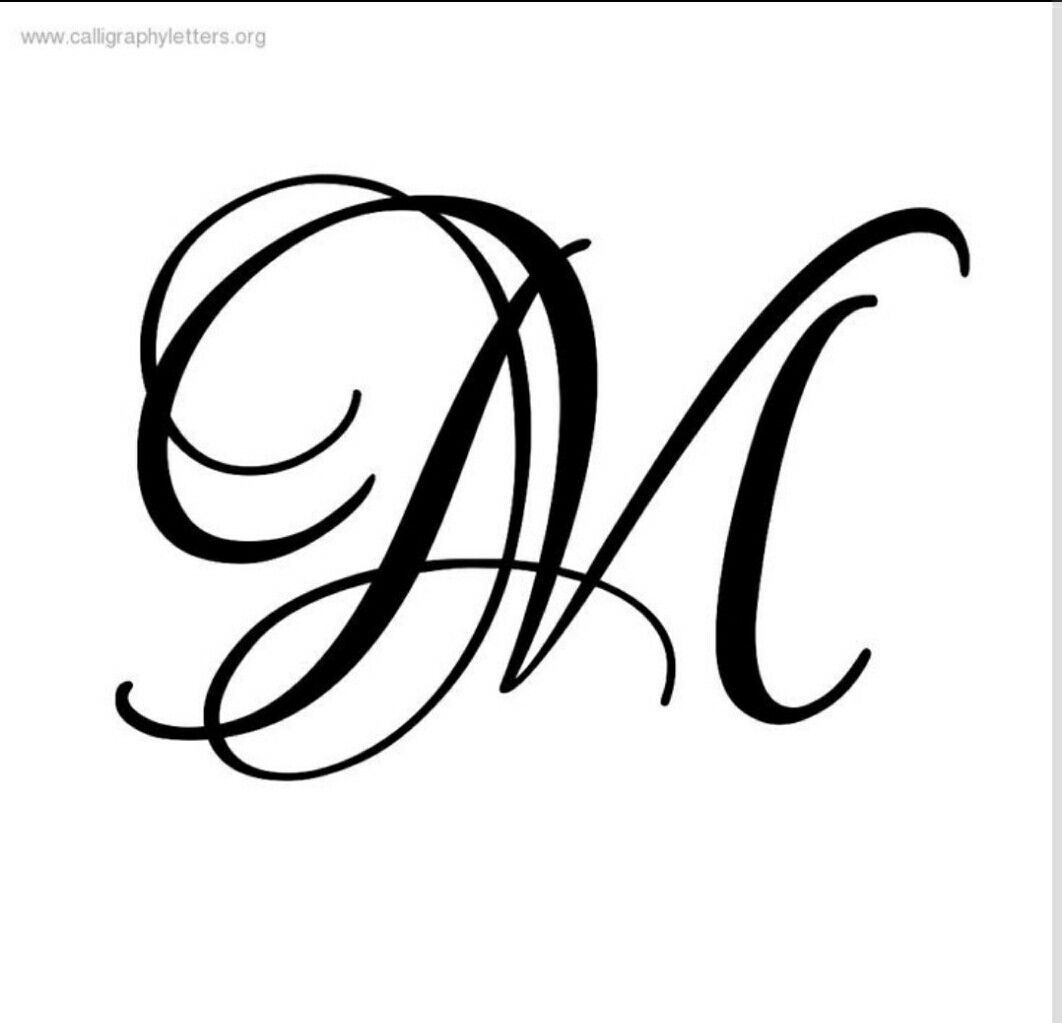
Как выбрать красивый шрифт для вашего онлайн-контента
Введение: Шрифты играют важную роль в эстетике и читабельности текста. Они могут воздействовать на наше восприятие информации и вызывать различные эмоции. В современном онлайн-контенте все больше людей обращают внимание на использование красивых шрифтов, чтобы сделать свой контент более привлекательным и запоминающимся.
1. Важность выбора правильного шрифта: Когда дело доходит до создания контента для веб-сайта, блога или социальных медиа, правильный выбор шрифта может повысить его эффективность и уникальность. Красивый шрифт поможет привлечь внимание читателей и сделать ваш контент более привлекательным.
2. Популярность использования красивых шрифтов: В последние годы наблюдается растущая
популярность использования красивых шрифтов в онлайн-контенте. Бренды, блогеры и дизайнеры все больше обращаются
к уникальным и привлекательным шрифтам, чтобы выделиться среди конкурентов и установить свой узнаваемый стиль.
3. Онлайн-сервисы по поиску и созданию шрифтов: Существует множество онлайн-сервисов, которые предлагают широкий выбор красивых шрифтов для использования в вашем онлайн-контенте. Некоторые из них предоставляют бесплатные шрифты, а другие — платные. Вы можете исследовать различные сервисы, чтобы найти идеальный шрифт, соответствующий вашему стилю и потребностям.
Как выбрать и использовать красивый шрифт
1. Определите свою аудиторию и цель: Перед выбором шрифта определите свою целевую аудиторию и цель вашего контента. Если ваша аудитория молодежь или веб-дизайнеры, то вы можете рассмотреть современные и стильные шрифты. Если ваш контент официальный или деловой, то лучше выбрать более классический и профессиональный шрифт.
2. Учитывайте читабельность: Независимо от выбранного шрифта, обязательно учтите его
читабельность. Шрифт должен быть легким для чтения и понимания.
Избегайте слишком узких или слишком декоративных
шрифтов, которые могут затруднять восприятие текста.
3. Используйте шрифты согласно их назначению: Некоторые шрифты лучше подходят для заголовков и выделения основных идей, в то время как другие шрифты лучше подходят для основного текста. Используйте разные шрифты, чтобы создать контраст и иерархию в вашем контенте.
4. Не перебарщивайте с количеством шрифтов: Важно не перегружать ваш контент слишком большим количеством шрифтов. Используйте 2-3 шрифта, которые хорошо сочетаются друг с другом и подходят для вашего стиля. Это поможет создать единый и профессиональный вид вашего контента.
5. Тестируйте и настраивайте: Перед публикацией вашего контента проверьте, как ваш выбранный
шрифт выглядит на различных устройствах и в разных размерах. Убедитесь, что шрифт хорошо читается как на
компьютере, так и на мобильных устройствах.
Как выбрать красивый шрифт для текстовых материалов
Введение: Значение выбора подходящего шрифта для текстовых материалов не следует недооценивать. Красивый шрифт может значительно повысить визуальное впечатление от текста и привлечь внимание читателя. В современном мире существует множество онлайн-ресурсов, где можно найти красивые шрифты на русском и английском языках. В этой статье я расскажу, как выбрать и использовать красивые шрифты для вашего текстового контента.
3. Инструкции по установке и использованию шрифтов: После выбора подходящего шрифта необходимо установить его на свой компьютер или веб-сайт. Для установки шрифта на компьютер обычно нужно скачать файл шрифта и добавить его в систему. Для использования шрифта на веб-сайте можно вставить специальный код или подключить его через сторонние сервисы. Каждый ресурс предоставляет инструкции и руководства по установке и использованию шрифтов.
Пример использования красивых шрифтов:
Ниже приведен пример кода для использования шрифта Lobster из Google Fonts на веб-сайте:
В данном примере мы подключаем шрифт Lobster через внешнюю таблицу стилей и применяем его к элементам селектора body. Теперь текст на веб-сайте будет отображаться шрифтом Lobster.
Красивый шрифт для социальных сетей
1. Популярность использования красивых шрифтов в Instagram: Instagram — одна из самых
популярных социальных сетей, где пользователи стремятся выделиться и привлечь внимание к своему контенту.